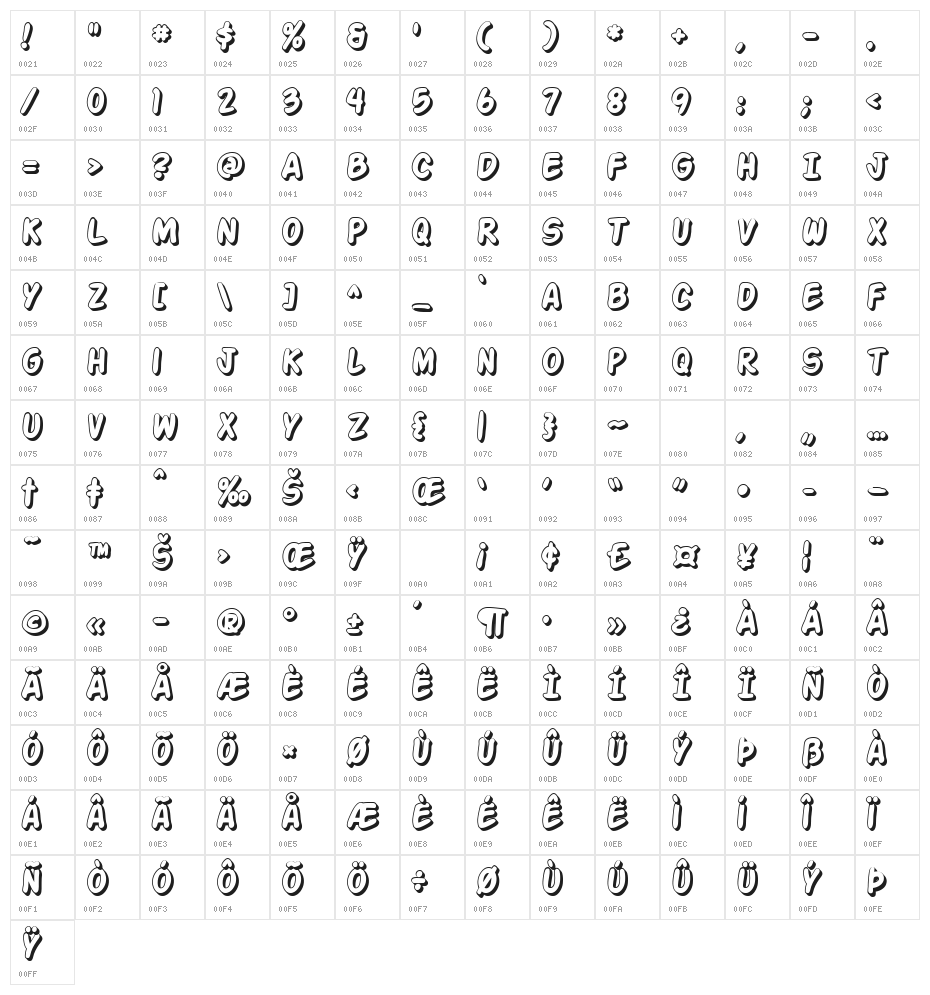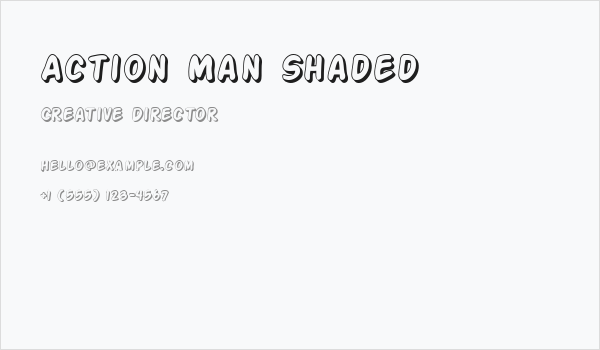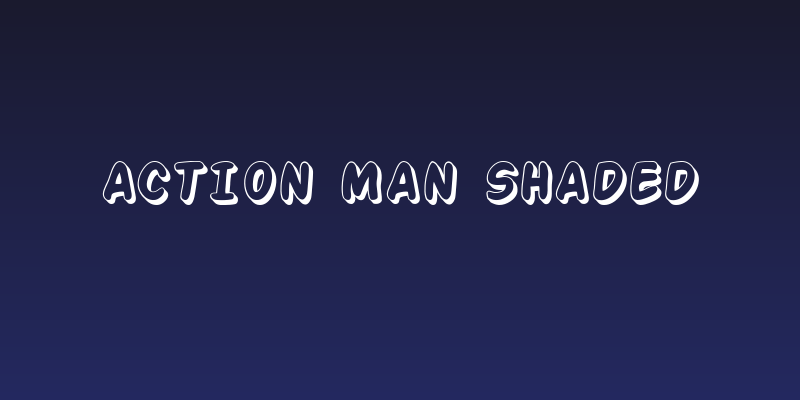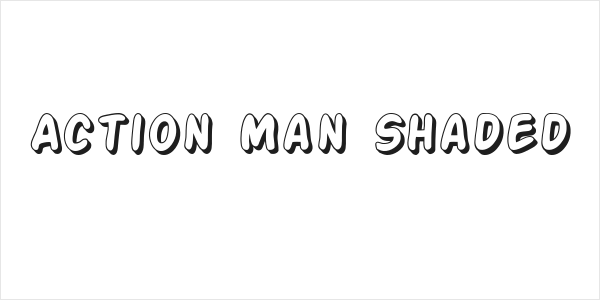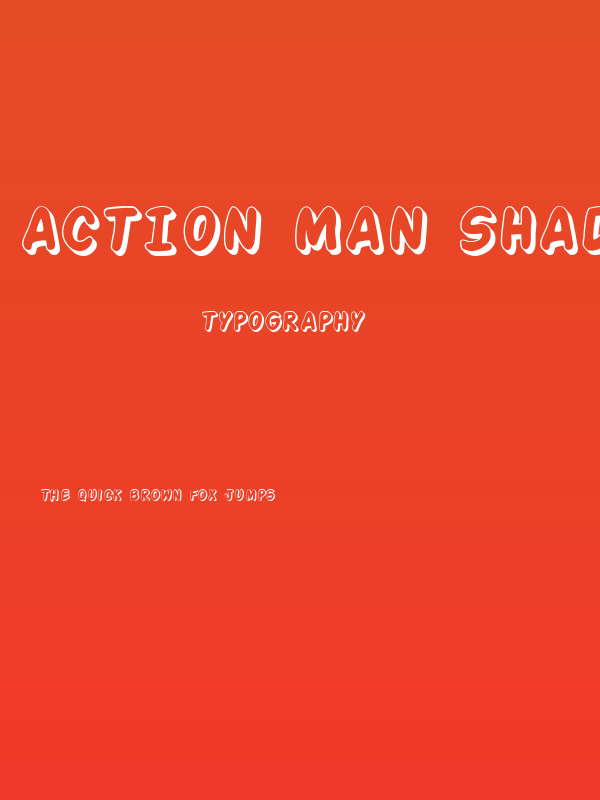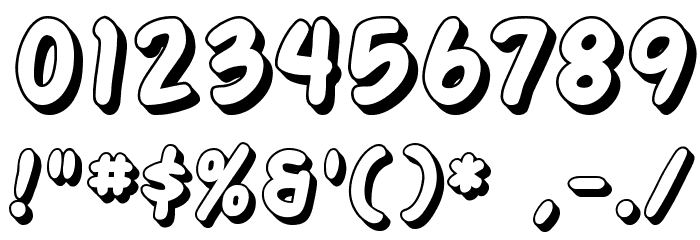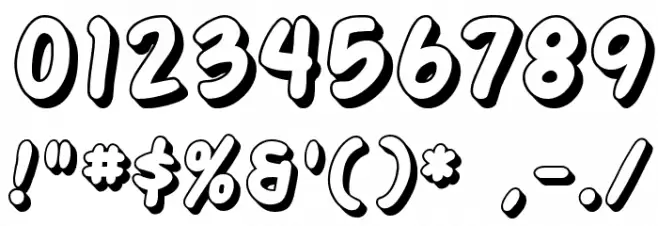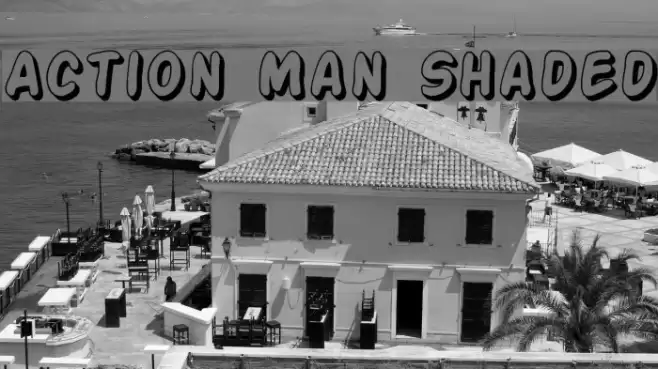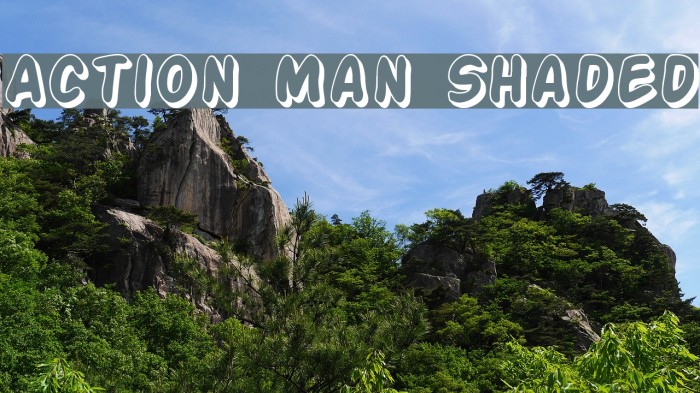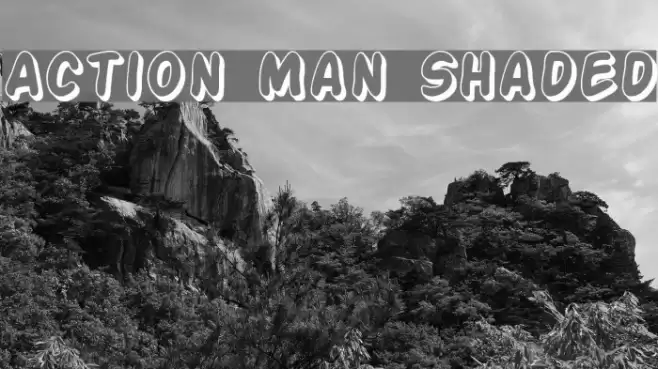
Action Man Shaded Font
| Estilo geral | Playful, Comic |
| Caso de uso | Headlines, Posters, Branding |
| Projetos propostos | Ideal for comic books, children's books, playful branding, posters, and any project requiring a fun and engaging typeface. |